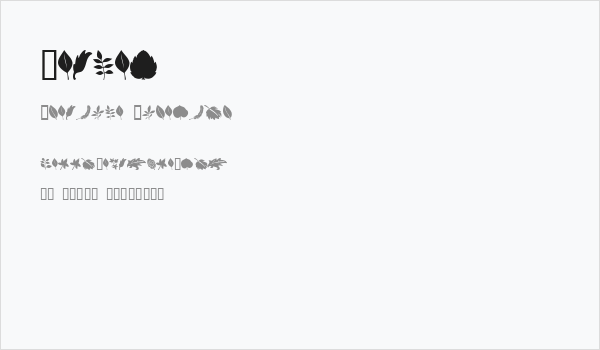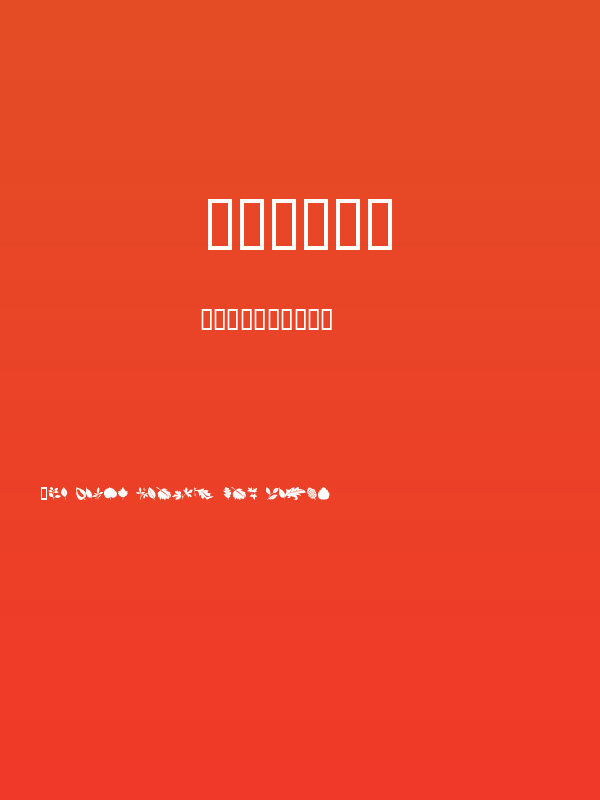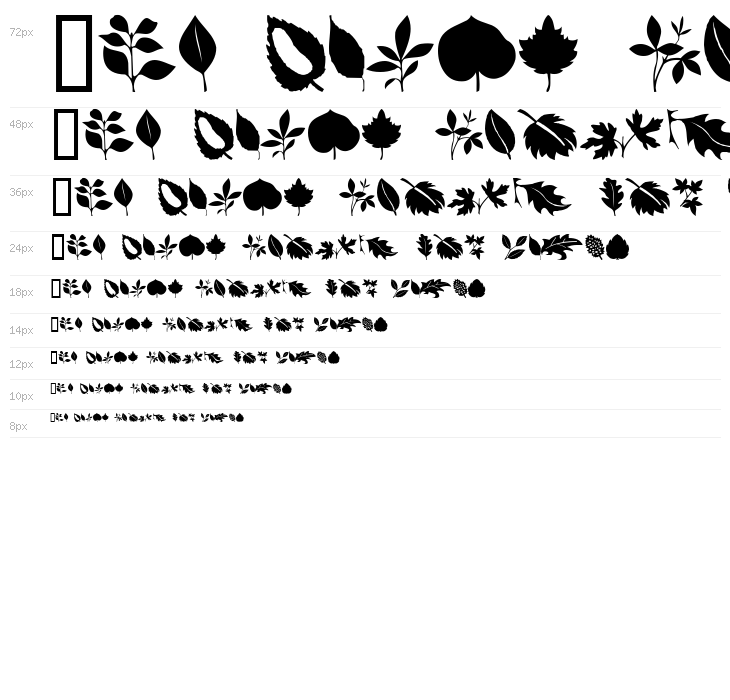
Leaves Font
| Gesamtstil | Decorative, Nature-inspired |
| Anwendungsfall | Logos, Decorative elements, Themed graphics |
| Vorgeschlagene Projekte | Nature-themed invitations, eco-friendly branding, educational materials, seasonal decorations, scrapbooking, and botanical illustrations. |